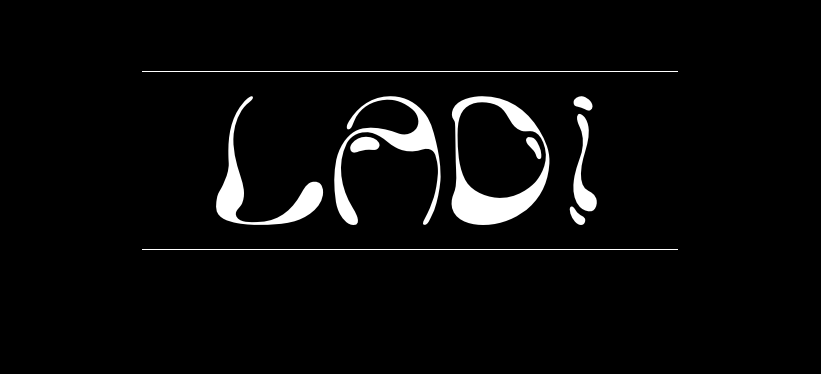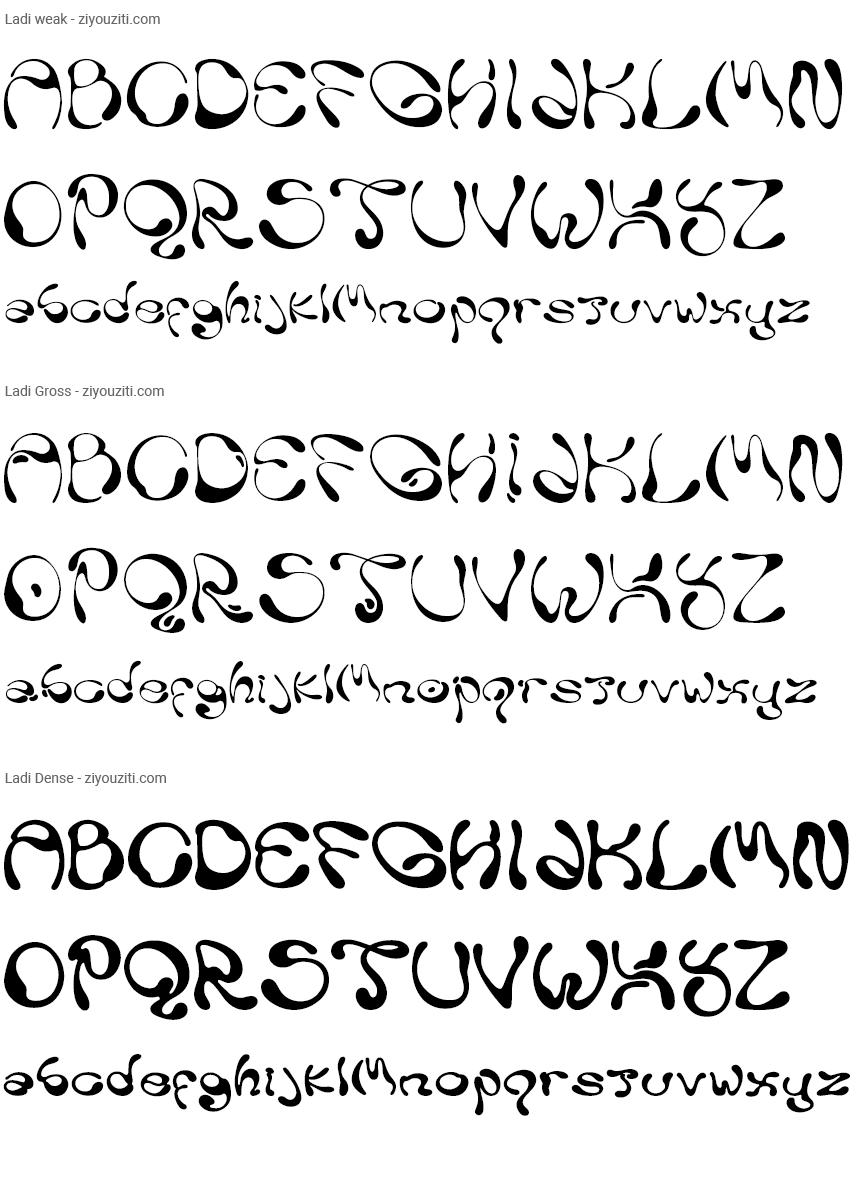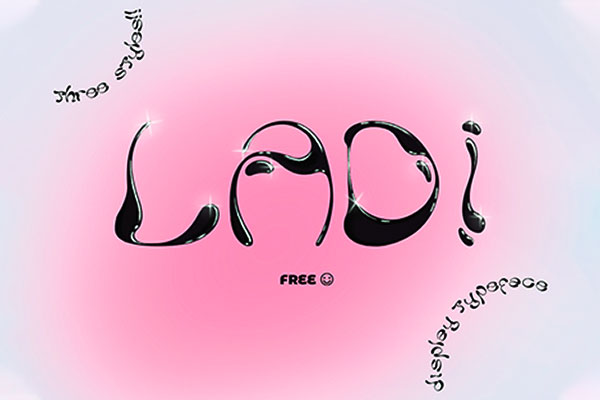
Ladi
Ladi的作者是巴西的Milena Leimig,Ladi的字形,是基于液体形式创作的不对称字体,以显示在其不平衡和不确定的曲线的高对比度。
Ladi字体的名字来自希腊语“λάδι”,意思是“油”,因为从字形的草图来看,粘性物质是最经常出现的参考,该字形旨在转化流动性,类似于悬浮在不断运动中的稠密液体。每个字母的形式都是对如何跟踪眼睛的单个路径进行的练习和实验,同时还像字母本身一样细心地塑造字形的空心空间。
Ladi是作者第一次尝试字体设计的作品,目前还没有设计数字部分,仅包含大小写字母,但是字母部分作者设计了3种不同的样式风格,大家可以选择适合自己的风格!